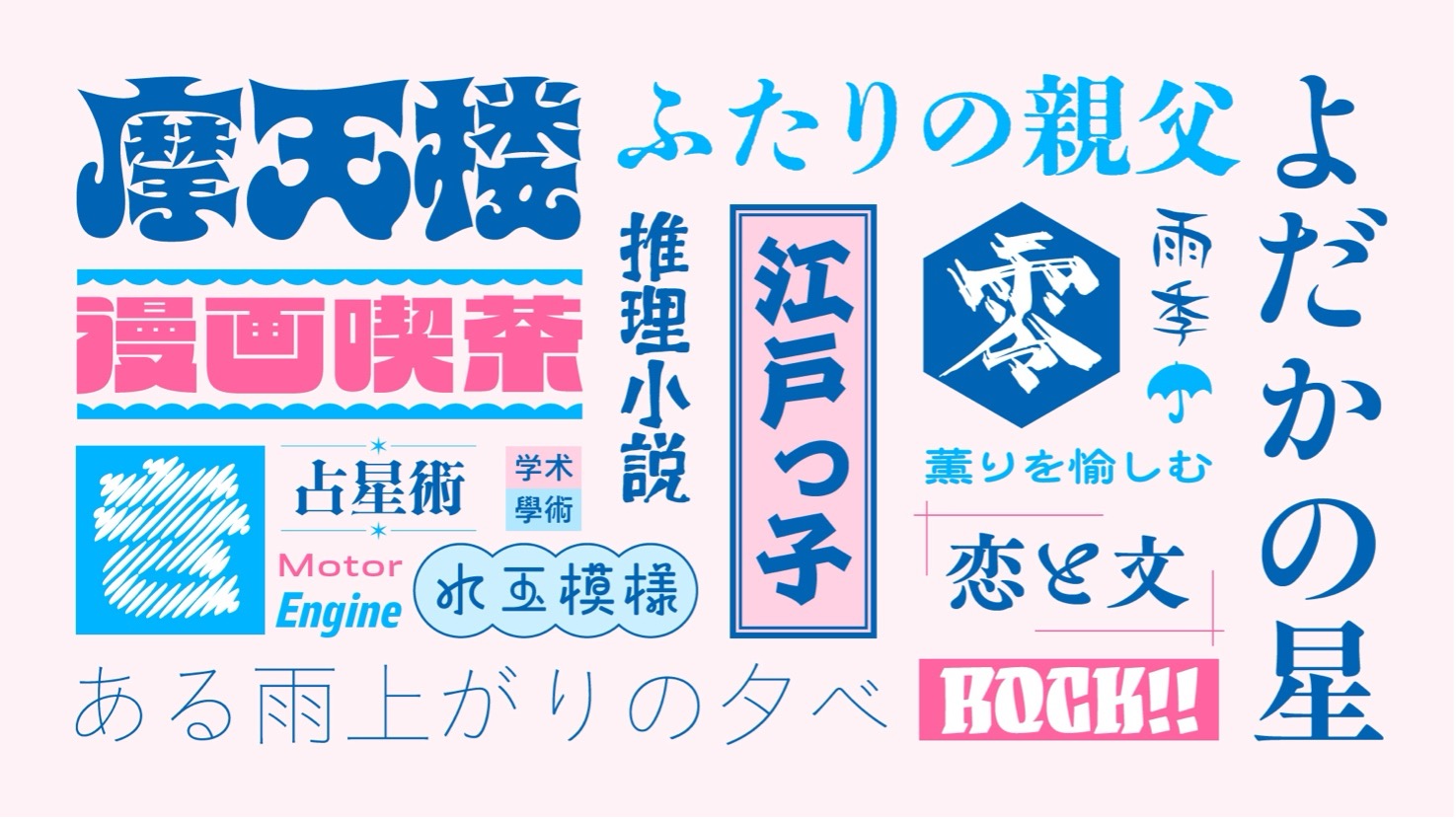
2024년 10월 15일(화)부터 타입스퀘어(TypeSquare) 웹폰트 서비스에 세계관 구축에 딱 맞는 일본어 디자인 서체 뿐만 아니라, 글로벌 시장에 대응할 수 있는 다국어 서체, 샤켄 폰트 등을 포함한 2024년도 신규 서체 160종이 추가되었습니다.
2024년도 신규 서체로는 사이키델릭 아트와 음악에서 영감을 받은 매우 두꺼운 서체인 「니지타코천국(虹蛸天国)」, 둥근 고리 장식이 즐거운 인상을 주는 「하루카제(はるかぜ)」, 에도 시대 문자를 모티브로 한 「테얀데(てやんでぇ)」 등 세계관 구축에 적합한 디자인 서체들이 출시됩니다.
또한, 서예가의 붓글씨를 기반으로 한 화려한 디자인의 「하나코오리(花氷)」 등 다양한 선택지가 추가됩니다. 명조체로는 2023년에 출시된 「케야키명조 올드스타일(欅明朝 Oldstyle)」의 제목용 서체 「케야키견출명조(欅見出明朝)」와 인기 있는 「슈에이니지미(秀英にじみ)」 시리즈의 「슈에이니지미초호명조(秀英にじみ初号明朝)」 등이 새롭게 추가됩니다. 또한 독특한 패밀리 구성이 특징인 「Heavy」 시리즈와 같이, 디자인에 포인트를 줄 수 있는 개성 있는 라틴알파벳 서체들도 주목할 만합니다.
그 외에도 글로벌 시장에 대응할 수 있는 다국어 폰트가 더욱 충실해 집니다. 올드스타일 고딕체인 「A1고딕(A1ゴシック)」에는 간체자와 번체자가 추가되며, 라틴알파벳 슈퍼 패밀리인 「Role」에는 인도와 동남아시아의 주요 문자에 대응하는 다국어 확장 패밀리가 새롭게 등장합니다.
또한, 히라기노(ヒラギノ) 폰트에는 인기 서체 「코부리나고딕(小ぶりなゴシック)」의 가장 얇은 웨이트인 W0이 추가됩니다. 더불어 주식회사 샤켄의 대표적인 서체를 OpenType 폰트로 수정한 「石井明朝 (이시이명조)」, 「石井明朝オールドスタイルかな(이시이명조 올드스타일가나)」, 「石井ゴシック(이시이고딕)」 외에도 「ゴナ(고나)」, 「ナール(나루)」 등 다양한 제목용 서체를 제공합니다.
2022년에 모리사와 그룹의 일원이 된, 대만을 대표하는 폰트 제조사 아픽(Arphic Types)에서는 중국어 표현을 더욱 풍부하게 할 수 있는 간체자 및 번체자 서체 라인업을 추가합니다. 간결하고 가독성이 높은 유니버설 디자인 서체인 「AR UDJingxiheiE1」와 부드러우면서도 힘찬 인상을 주는 「AR ShuYuanSong Text H32」 등 아픽의 대표 서체가 새롭게 추가됩니다.
또한, 따뜻함과 리드미컬한 움직임을 표현한 「AR Mochi H16C90」와 미래지향적인 분위기의 「AR Xinyi」는 「스이류(翠流)」 시리즈의 기반이 된 서체들입니다. 일본어 서체인 「스이류키라보시(翠流きら星)」와 「스이류아틀라스(翠流アトラス)」 등과 함께 사용하면, 일본어와 중국어를 모두 필요로 하는 상황에서 디자인의 통일감을 유지할 수 있습니다.
미국에 기반을 둔 오큐판트폰트(Occupant Fonts)의 라틴알파벳 서체 라이브러리도 추가됩니다. 오큐판트폰트는 오랜 경력을 지닌 타입 디자이너이자, 2017년부터 모리사와 USA의 크리에이티브 디렉터로 활약 중인 사이러스 하이스미스(Cyrus Highsmith)가 이끄는 서체 라이브러리입니다.
눈길을 사로잡는 화려한 디스플레이 서체인 「Occupant Gothic」과 「Biscotti」 등 다양한 라인업이 추가됩니다. 영문 조판의 선택지가 늘어날 뿐만 아니라, 일본어 서체와 혼합하거나 함께 사용하는 경우에도 표현의 폭이 한층 더 넓어집니다.